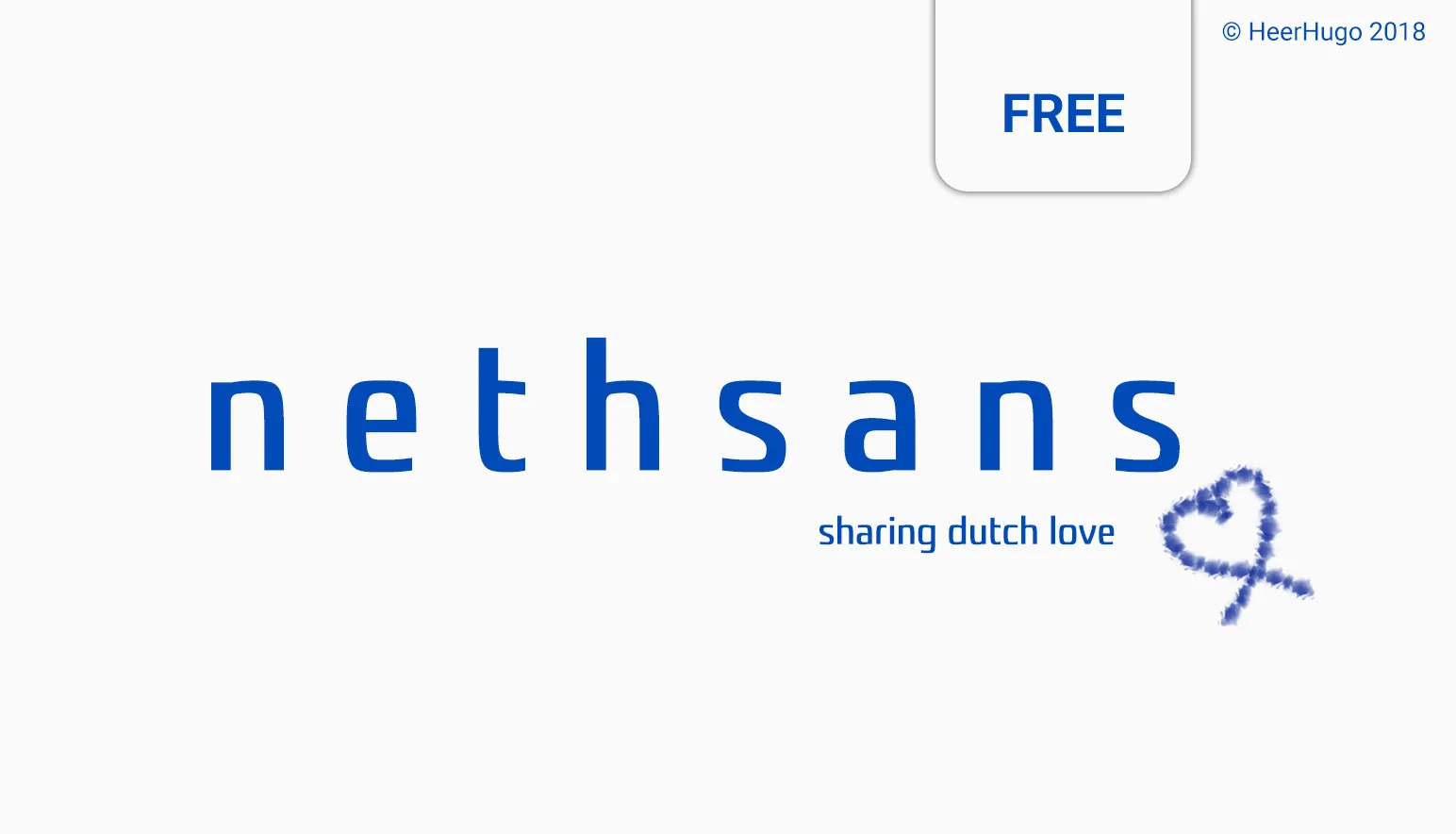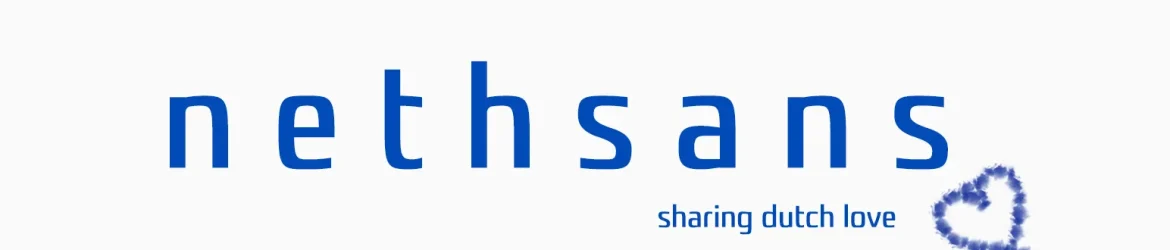
Nethsans Typeface – Entirely Free – Download Grátis
A Nethsans Typeface é uma fonte sans-serif completamente gratuita para uso pessoal e comercial. Seu nome é resultado de “neth”, que remete à Holanda e “sans”, indicando estilo de serifas. Esta fonte adota um visual futurista, apesar de ter um conjunto de caracteres bastante restrito. O projeto originalmente surgiu como uma curiosa experimentação, com cerca de 40% das letras geradas por um algoritmo de inteligência artificial. A implementação do software dedicado ao seu design e à sua composição exigiu significativos tempos. Apesar disso, ainda não é viável automatizar a geração completa de família de fontes desta maneira. Por enquanto, o processo exige que eu carregue ou copie as fontes para FontLab, ajuste os parâmetros ótimos, modifique e preencha os settings. Embora seja lento no momento, o projeto tem potencial para evoluir e tornar-se mais eficiente com o tempo.